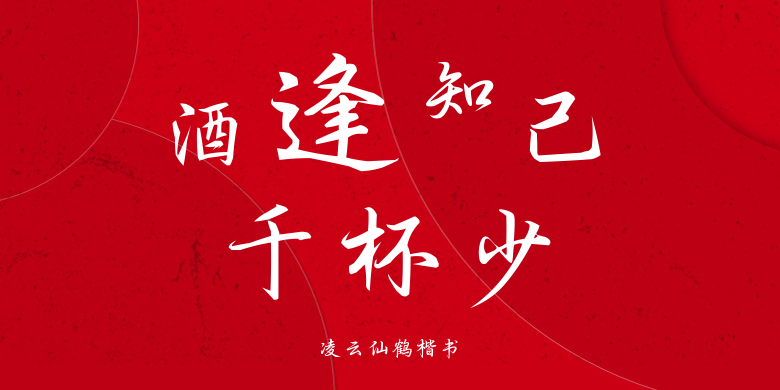
凌云仙鹤楷书
凌云仙鹤楷书,这款字体结构工整、笔画清晰,兼顾美观与易读性,适用于标题、正文、海报、包装、LOGO 等多种场景。字形优雅稳定,风格百搭耐看,适配日常排版与创意设计,让文字呈现更舒适、更具质感。凌云仙鹤楷书一笔一画,皆是细节,以均衡的比例、流畅的线条打造舒适视觉体验,字形端正大气,风格简约现代。无论是商业设计、品牌宣传还是日常排版,都能轻松驾驭,让文字更有格调与力量。凌云仙鹤楷书字体下载。